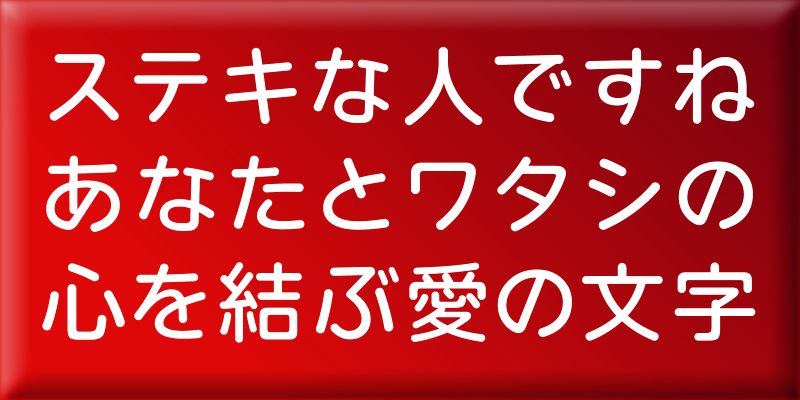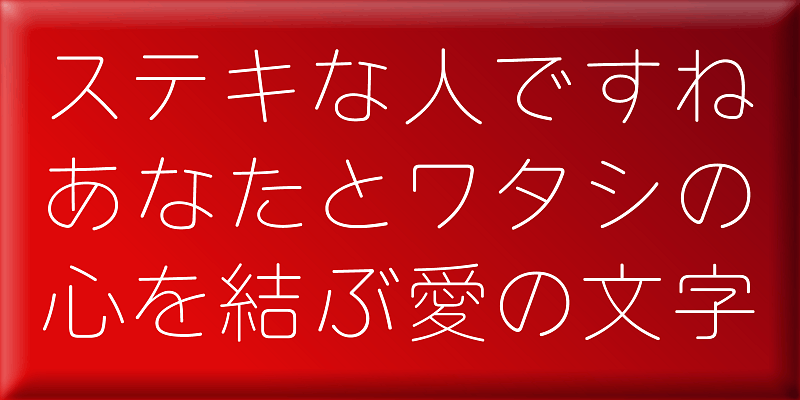
WanpakuRera-4 kombiniert die „Wanpakumaru“, eine klare, erfrischende und freundliche gotische Rundschrift, mit der „Rera“, einer einfachen gotischen Rundschrift. Ihr klares und energiegeladenes Design verleiht dem Text einen lässigen Look.